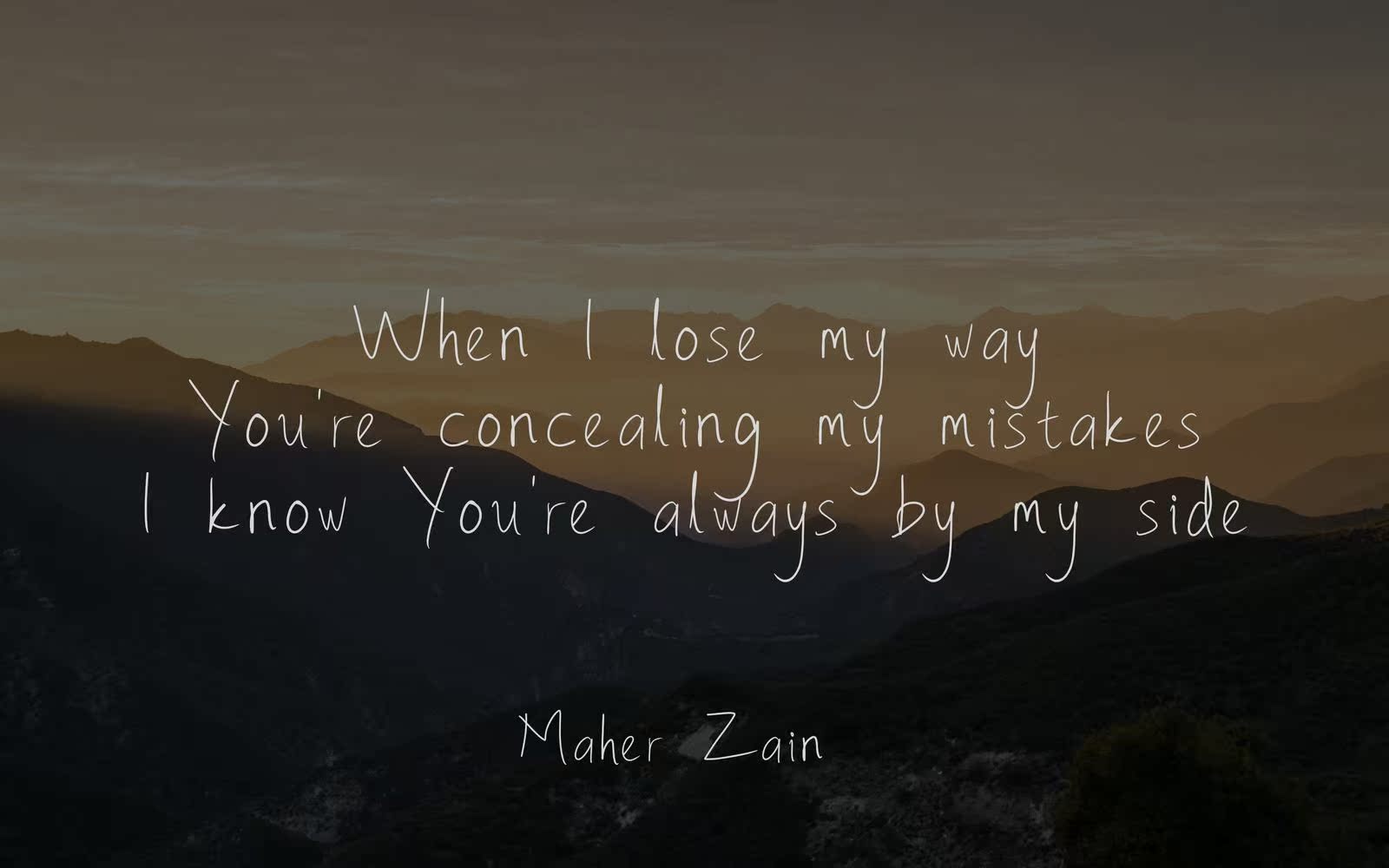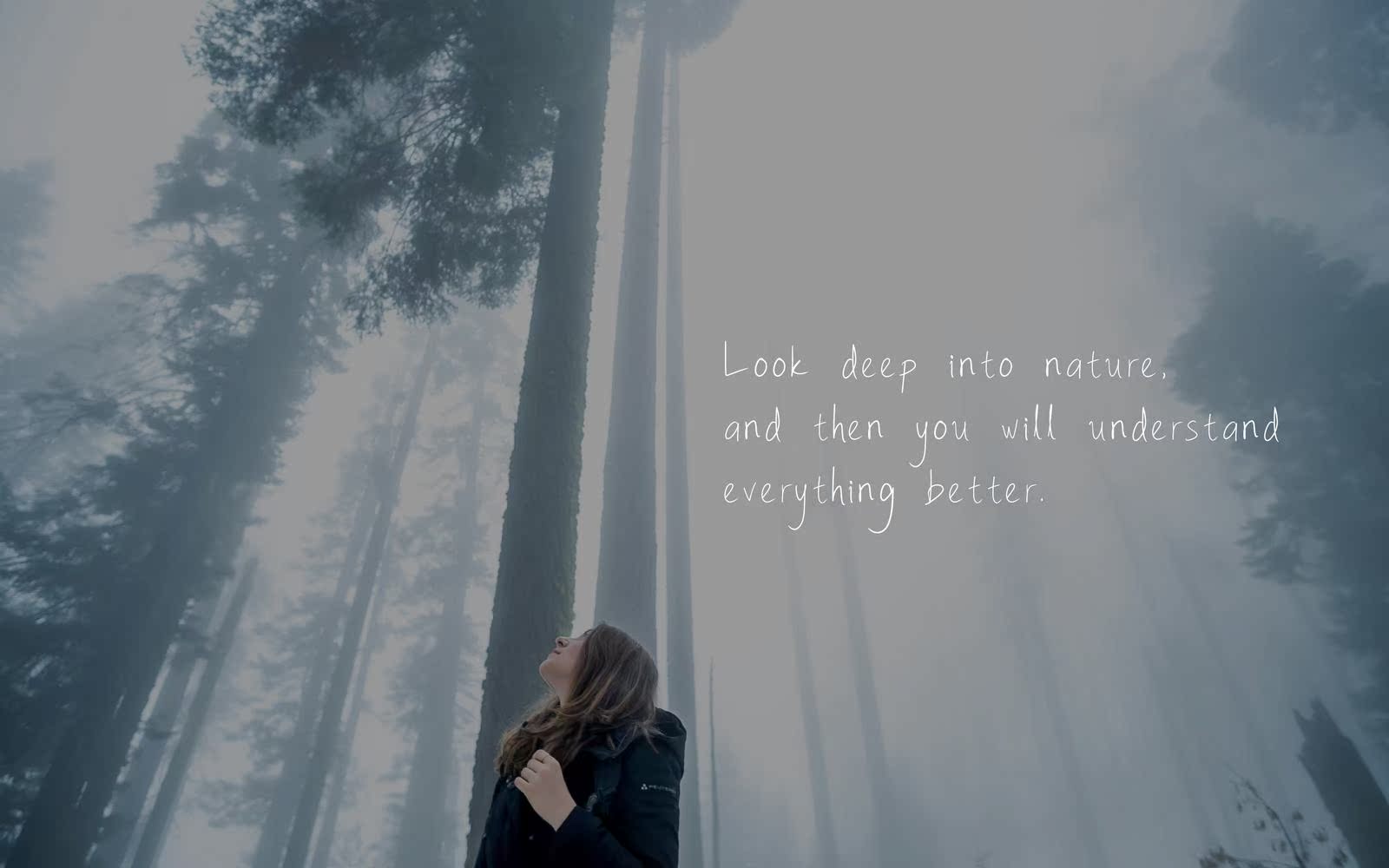
Acakadul手写体是一种独特友好的手写体,具有独特的伤害。具有快速干笔和签名风格。Acakadul适用于品牌项目、家居设计、,产品包装–或简单的文字覆盖任何背景图像。Acakadul手写体是一种独特且友好的手写体,具有个人伤害。具有快速干笔和签名风格。Acakadul适用于品牌项目、家居设计、产品包装–或简单的文字覆盖任何背景图像。